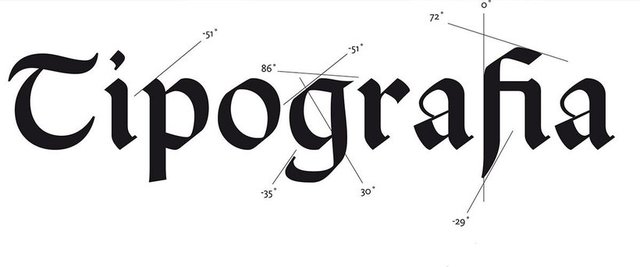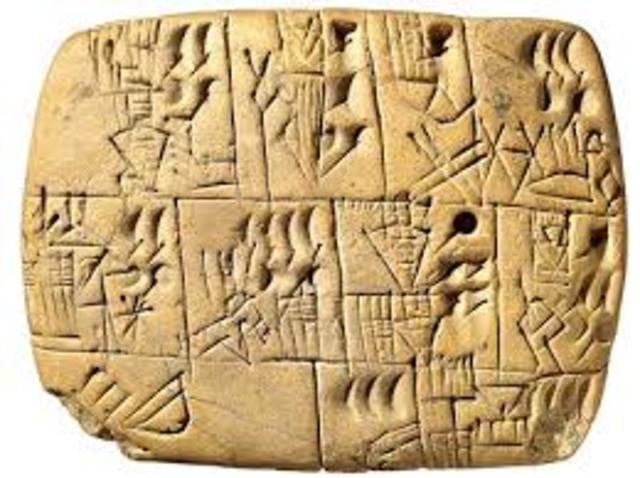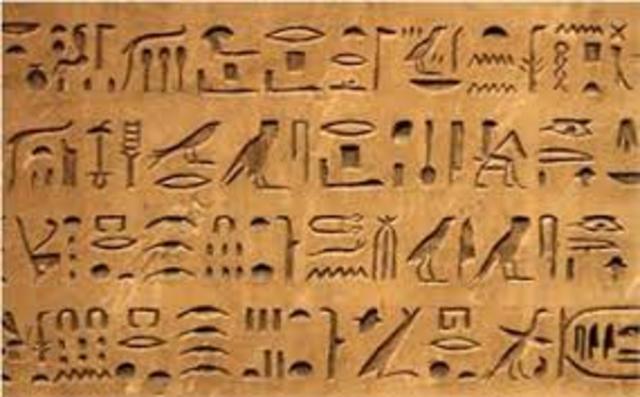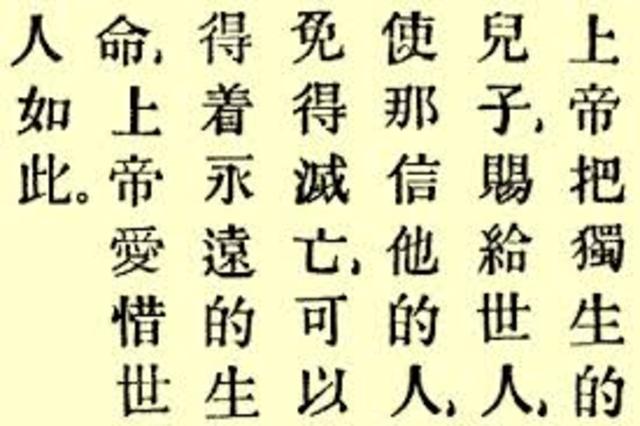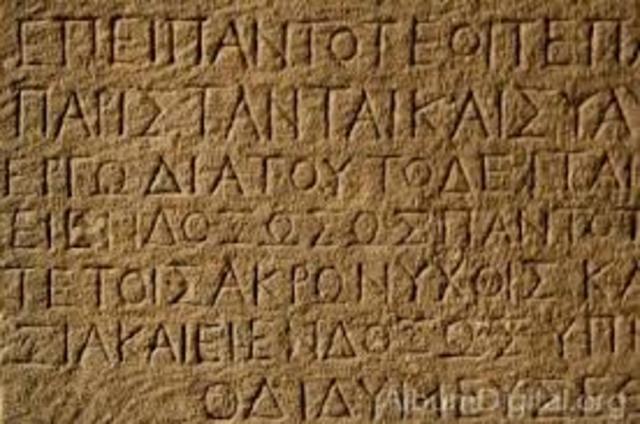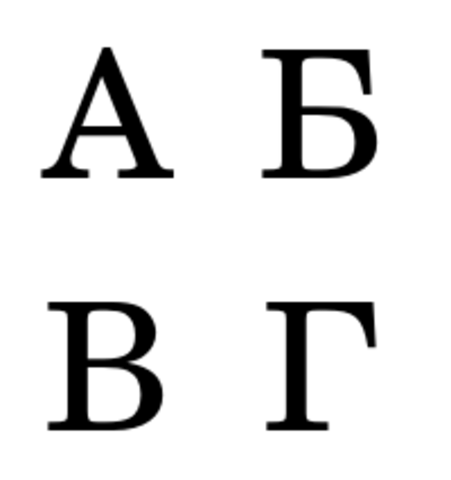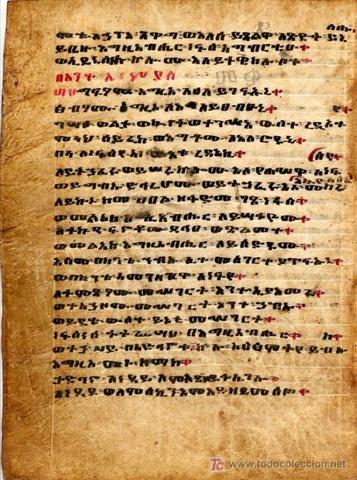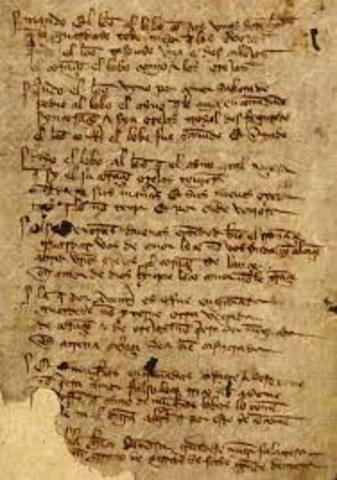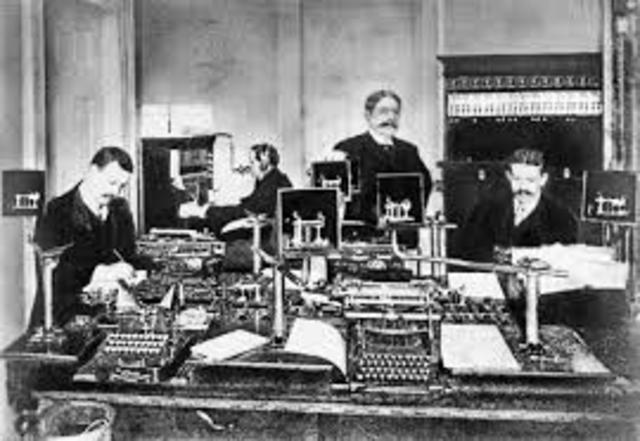
4000-100 a.C.
Se desarrolló en la antigua Mesopotamia y se elaboraba en tablas de arcilla húmeda con estiletes en forma de cuña. Se transformó en renglones escritos de derecha a izquierda, se ladearon los signos. Desaparece en los siglos VI y VII a.C. con la escritura fenicia. -
3.300 a.C.-394
Se basa en pictogramas los cuales representan un objeto en lugar de un sonido vocal. Se escriben de derecha a izquierda, de izquierda a derecha o de forma descendente. Se crea el concepto de código y los símbolos, creación del papiro. -
(S. XIX)
Creación papel pergamino, letra capital y gótica -
(940)
Se utiliza en la escritura de 6 lenguas eslavas, en la antigua Unión soviética, Asia, Europa del Este y contiene 33 letras. En la edad media, las letras de éste sistema eran muy altas y estrechas. Las letras cirílicas actuales con parecidas a las latinas actuales. -
(800 a.C.)
Adoptaron caracteres del sistema fenicio y desarrollaron su propio alfabeto. En el griego antiguo se empieza a escribir de izquierda a derecha y en la línea siguiente de derecha a izquierda y se va alternando (bustrófedon). Con la invención de los signos de puntuación, pasó a ser un sistema de escritura de izquierda a derecha. Espacio entre signos para generar silencios, tamaño y dirección de los caracteres. -
En la escritura China, existe un símbolo que distingue a cada palabra; Ideogramas que representaban sonidos en lugar de conceptos. Dio lugar a la creación de una escritura denominada "caligrafía del pequeño sello" (206 a.C. - 220 a.C.).
Consta de 26 letras y se formó a partir del alfabeto griego. Cada letra representaba un valor numérico. Crearon una tabla de cera que permitía borrar, se crearon las mayúsculas.
(900 a.C.)
El arameo es precursor del árabe y hebreo y fue difundido por el imperio asirio y posteriormente fue sustituido por el alfabeto árabe y hebreo. El alfabeto árabe se lee de derecha a izquierda y está compuesto por 22 consonantes. -
(1600 a.C.). Los fenicios establecen fundamentos del alfabeto latino actual, sistema de 22 símbolos que representaban sonidos en vez de objetos. Escribían en forma horizontal de derecha a izquierda. Los fenicios dieron origen a escrituras como la hebrea, árabe, griega y latín. Dan inicio al alfabeto y a los signos de puntuación.
( S. XVIII)
Aceleración de procesos de impresión (fotograbado). Sistema de medición tipográfico basado en puntos. Introducción de la "negrita", creación de la litografía, linotipia, punzón y monotipia.